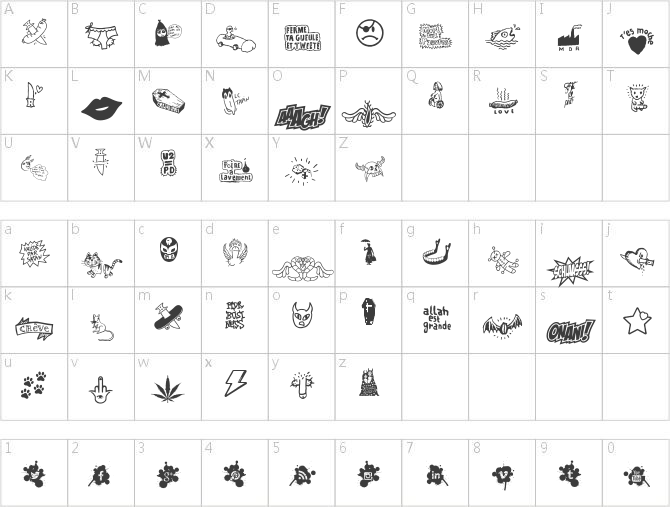
WC_Schlaasss_Classic
WC_Schlaasss_Classic介紹
WC_Schlaasss_Classic字體字庫(kù)是一款讓人賞心悅目、百看不厭的英文字體,適合各類(lèi)廣告和產(chǎn)品包裝設(shè)計(jì)應(yīng)用,字體大小0.74MB,格式為ttf字體,上傳用戶(hù)是速拓科技,作者/版權(quán)方為未知